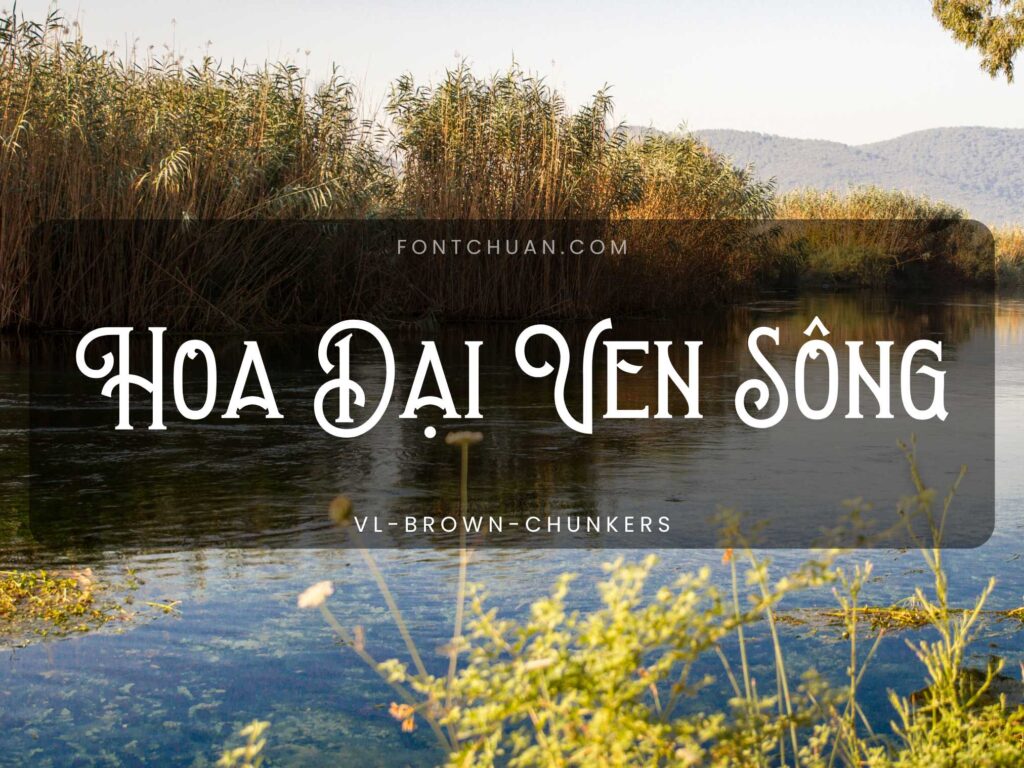
Font VL Brown Chunkers Việt Hóa
Tác giả Font: Letterhend Studio
Việt hóa bởi: Font Việt Linh
VL-Brown-Chunkers là một phông chữ hiển thị mang phong cách cổ điển, được thiết kế bởi Letterhend Studio. Phông chữ này có các nét đậm và hình dáng độc đáo, tạo nên sự ấn tượng và thu hút cho các thiết kế. VL-Brown-Chunkers đã được Việt hóa bởi Việt Linh, hỗ trợ đầy đủ các ký tự tiếng Việt, giúp người dùng dễ dàng sử dụng trong các dự án sáng tạo. Phông chữ này được thành viên Font Chuẩn sưu tầm và đăng tải nhằm phục vụ nhu cầu thiết kế đa dạng.
Với thiết kế độc đáo và nổi bật, VL-Brown-Chunkers phù hợp cho các ứng dụng như tiêu đề, áp phích, thiết kế logo và các ấn phẩm truyền thông. Trong lĩnh vực sự kiện, phông chữ này có thể được sử dụng trong các dịp như lễ hội, sự kiện âm nhạc và các chương trình giải trí. Ngoài ra, VL-Brown-Chunkers cũng thích hợp cho các ngành nghề như quảng cáo, truyền thông và thiết kế đồ họa.